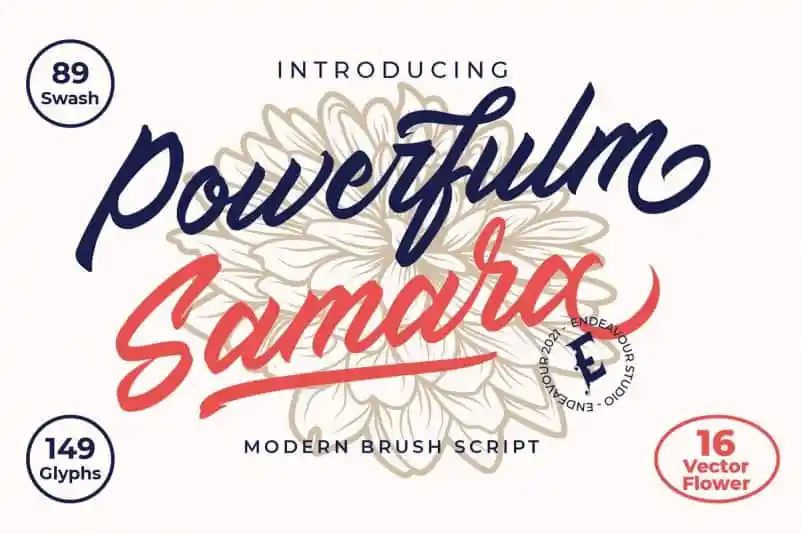
Powerfulm Samara Script Font – Download Grátis
Powerfulm Samara Script é uma elegante e única fonte que combina influências de letra aquarela com elementos florais vectoriais. Foi criada pelo designer Endeavour Studio, conhecido por suas criações de tipografia simples mas poderosas. Esta font pode ser usada em diversos projetos relacionados à moda, como roupas, tops e embalagens, além de aplicações para logotipos, cartões de visita, postais, identidades visuais, maquetes gráficas e qualquer outro tipo de projeto que exija uma textura sofisticada. Suas bordas suaves e detalhes refinados tornam ela perfeita tanto para uso individual quanto em coleções amplas, garantindo um toque especial a seus trabalhos gráficos. O poder dessa font reside não apenas em sua aparência, mas também em seu potencial de transformar qualquer projeto em algo único e memorável.